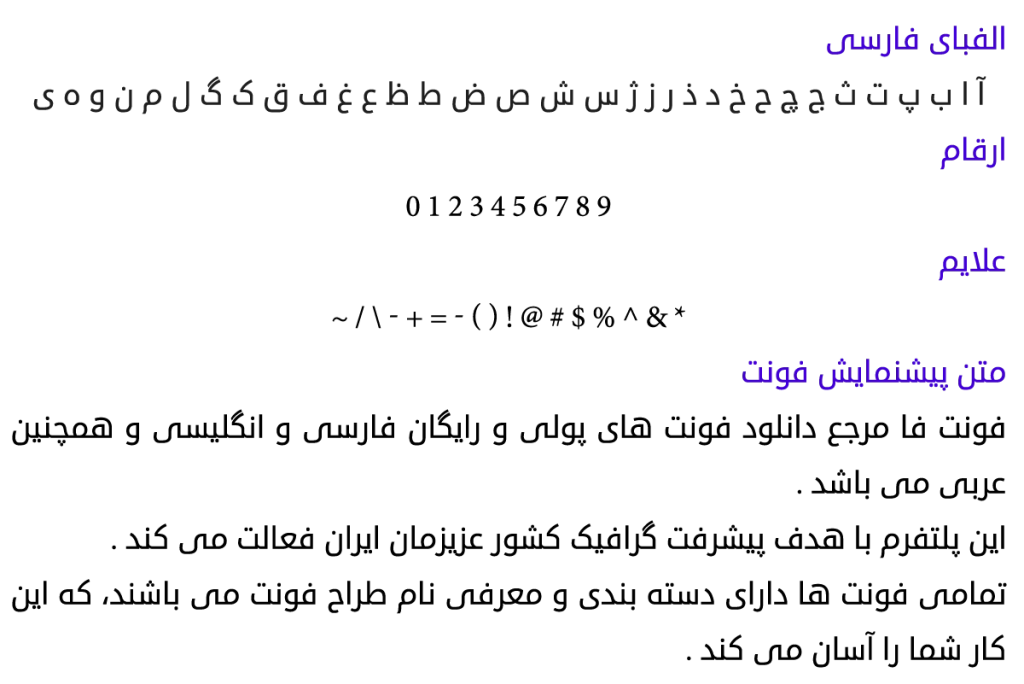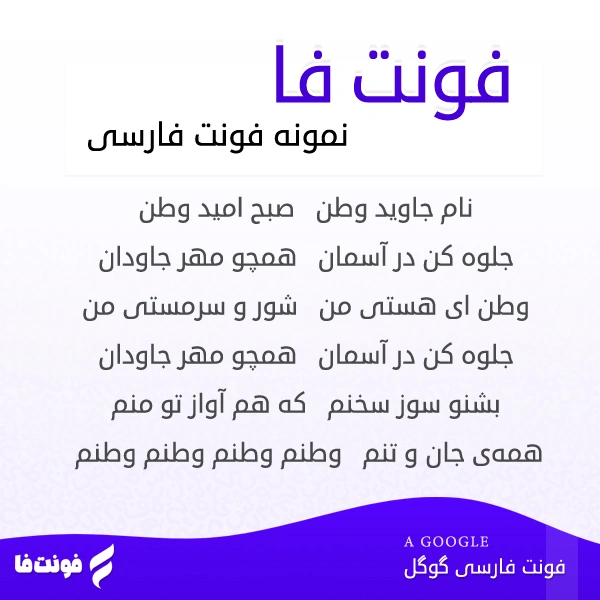
فونت فارسی گوگل – A Google
طراح فونت: ابراهیم شفیعی نوع فونت: فونت متن
توضیحات و معرفی فونت گوگل
فونت فارسی گوگل ( A Google ) از مجموعه فونت های آزاد می باشد، همچنین نوع فونت متن می باشد.
فونت فوق العاده زیبای معرفی شده در سال 1390 طراحی و ساخته شده است.
همچنین فونت A Google در یک وزن معمولی است.
در لیست زیر می توانید وزن این فونت فوق العاده زیبا را ببینید.
- A Google Regular
در تصویر زیر میتوانید شعر دلنشین «نام جاوید وطن» را ببینید که با این تایپ فیس فارسی طراحی شده است.